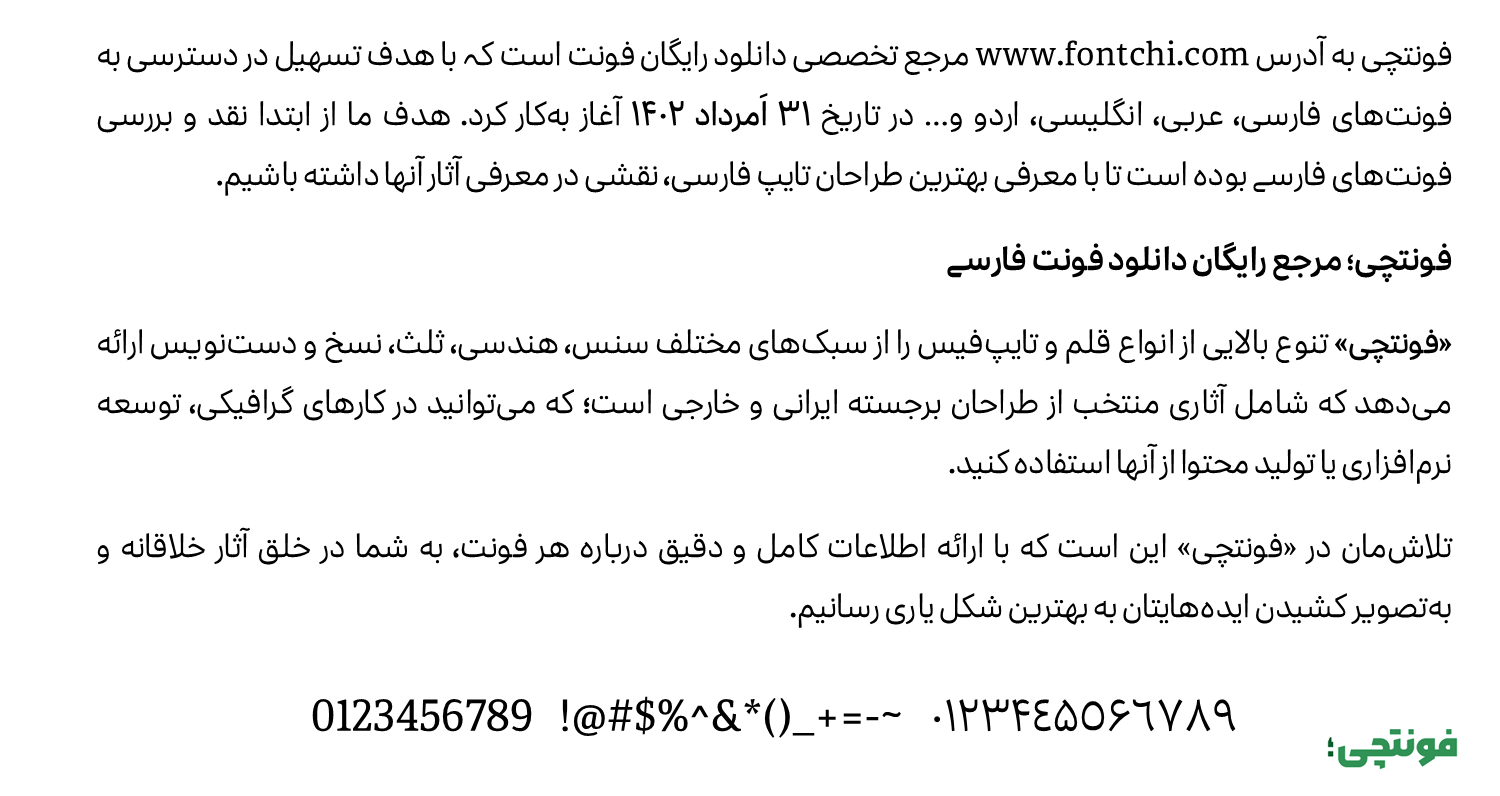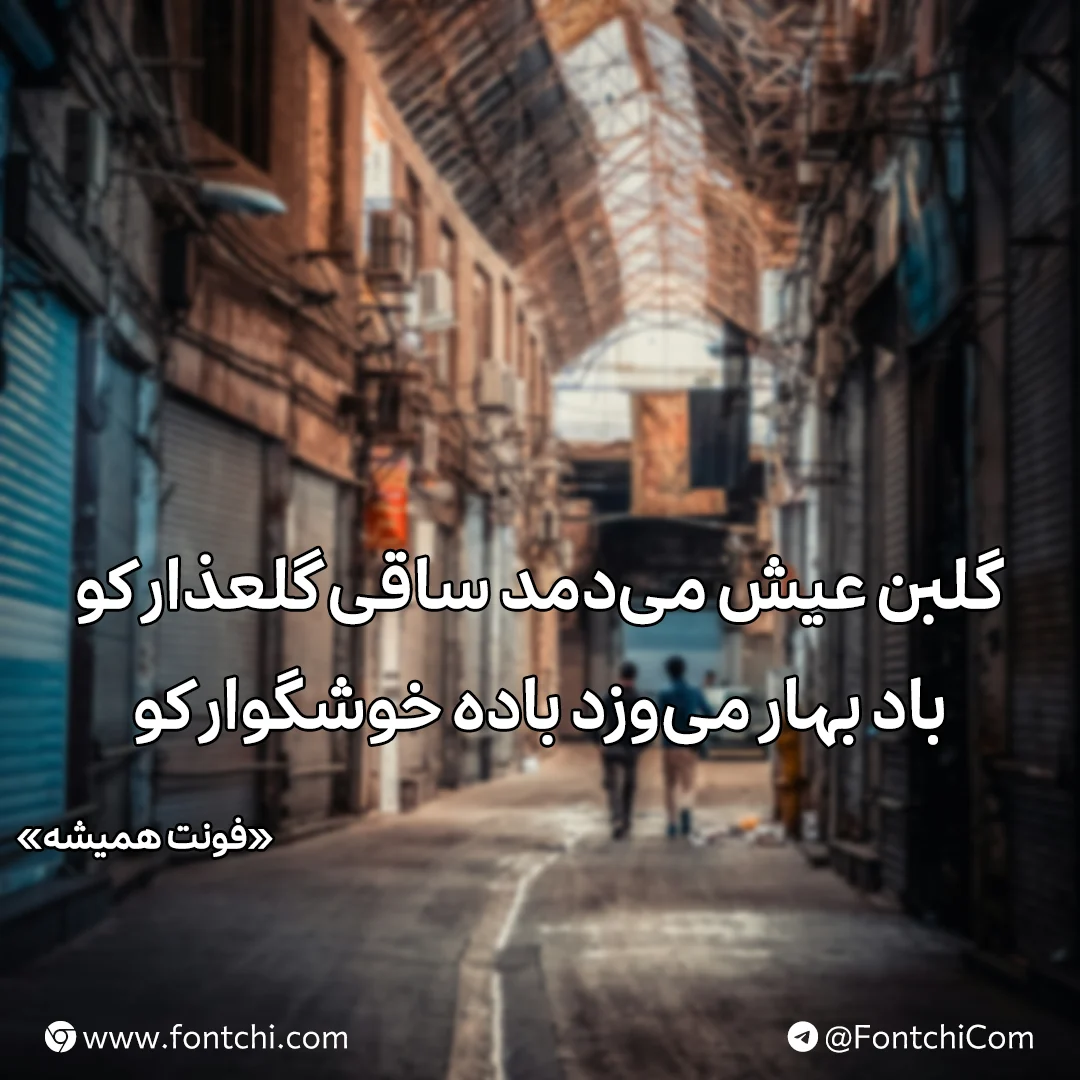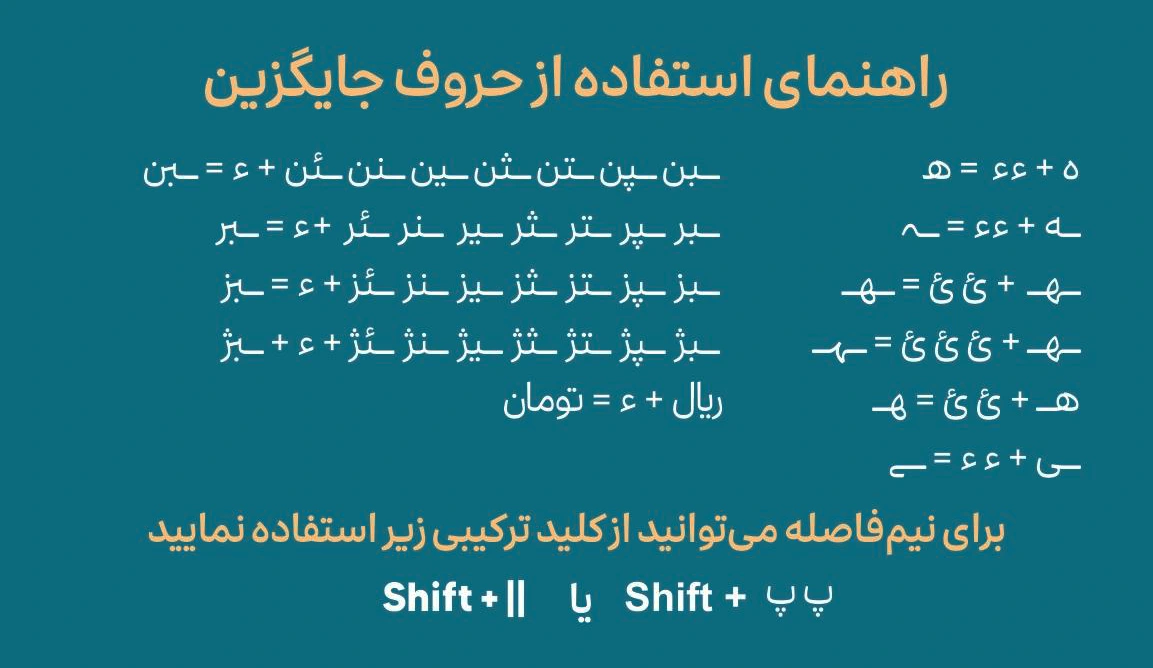
فونت دیجی همیشه (Digi Hamishe)
فونت همیشه یا فونت دیجی همیشه (به انگلیسی: Digi Hamishe) قلمی به سبک سنس است که از دو وزن معمولی و بولد طراحی شده است. این فونت رایگان فارسی که از حروف جایگزین و اعداد استاندارد فارسی و عربی پشتیبانی میکند، برای استفاده در متون بلند و کوتاه مناسب است.
طراح این فونت مهدی برقگیر است که مجموعه سری فونتهای دیجی فونت از دیگر آثار وی است. با توجه به حس نیازی که برای فونت متون به سبک مدرن وجود داشت، این قلم را برای استفاده در نشریههای دیجیتال طراحی نمود. در ادامه با نقد و بررسی این قلم همراهتان هستیم.
فونت دیجی همیشه با رعایت استانداردهای حرفهای فونتهای فارسی، خوانایی فوقالعادهای دارد. این ویژگی، آن را برای متون طولانی مانند مقالات، کتابها یا حتی زیرنویسهای ویدئویی مناسب میکند. اعرابگذاری هوشمند و کرنینگ متعادل، از بههمریختگی حروف جلوگیری کرده و تجربهای روان برای خواننده فراهم میآورد.
این فونت فارسی از زبانهای دیگری همچون عربی، کردی، اردو و انگلیسی پشتیبانی میکند. پشتیبانی از زبانها در سطح بالایی رعایت شده که شامل اعراب، کاراکترهای خاص و اعداد است. بهطوری که در این فونت از اعداد استاندارد فارسی و عربی برای هر زبان استفاده شده است.
فونت دیجی همیشه را میتوان قلمی با دو روح توصیف کرد:
- از یک سو، خوانایی و استاندارد بودن آن، این فونت را برای متون رسمی و دانشگاهی مناسب میکند.
- از سوی دیگر، صمیمیت و انعطافپذیریاش، آن را به گزینهای ایدهآل برای طراحیهای خلاقانه و شبکههای اجتماعی تبدیل میکند.
این فونت که در دو وزن معمولی (Regular) و بولد (Bold) عرضه شده، به طراحان امکان میدهد بسته به نیاز پروژه، بین ظرافت و قدرت انتخاب کنند.
ساختار فونت همیشه شباهتهایی به فونت محبوب ایران یکان دارد، اما با چاشنیای از گرما و دوستی که آن را متمایز میکند. حروف این فونت، با انحناهای نرم و کنتراست مناسب، حس تعادل را به چشم میآورند.
از طراحی کاور پستهای اینستاگرام گرفته تا عناوین مجلات و حتی متنهای فانتزی و عاشقانه؛ میتوانید از این فونت بهره کافی را ببرید. پشتیبانی از زبان کردی نیز یک امتیاز ویژه برای کاربرانی است که به تنوع زبانی نیاز دارند. از سایر کاربردهای این قلم میتوان به موارد زیر اشاره کرد:
- شبکههای اجتماعی: برای طراحی استوریهای اینستاگرام، کاور پستها یا حتی نقلقولهای انگیزشی، دیجی همیشه با حس صمیمی خود جلبتوجه میکند.
- طراحی گرافیکی: از پوسترهای تبلیغاتی تا بنرهای وبسایت، این فونت به دلیل خوانایی و زیبایی، انتخابی مطمئن است.
- نشر دیجیتال و چاپی: برای کتابها، مجلات یا حتی بروشورها، وزن ساده فونت برای بدنه متن و وزن بولد برای عناوین، ترکیبی حرفهای ایجاد میکند.
- پروژههای فانتزی و هنری: با استفاده از حروف جایگزین، میتوانید تایپوگرافیهای خلاقانهای برای لوگوتایپ یا آثار هنری دیجیتال خلق کنید.
ترکیبات و حروف جایگزین فونت همیشه
وجود حروف جایگزین متعدد و لیگیچرهای متنوع، به طراحان اجازه میدهد تا متون خود را خلاقیت در تایپوگرافی کاملتر کنند. این ویژگیها، دیجی همیشه را به فونتی هوشمند و پویا تبدیل کرده که میتواند در هر پروژهای، از پوسترهای تبلیغاتی گرفته تا استوریهای اینستاگرام، مناسب کند.
کافی است بر اساس راهنمای زیر با استفاده از دو کاراکتر ترکیبی «ء، ئ» برخی کلمات را با ظاهری متفاوت تایپ کنید. این ظاهر متفاوت در کارهای نمایشی یا تبلیغاتی باعث افزایش جلب توجه مخاطب خواهد شد.
ناگفته نماند که این فونت نسبتا به فونت آیفون نیز شباهت دارد که در صورت نیاز به جایگزینی که برای همه زبانها قابل استفاده باشد میتوانید از این قلم بهره ببرید.